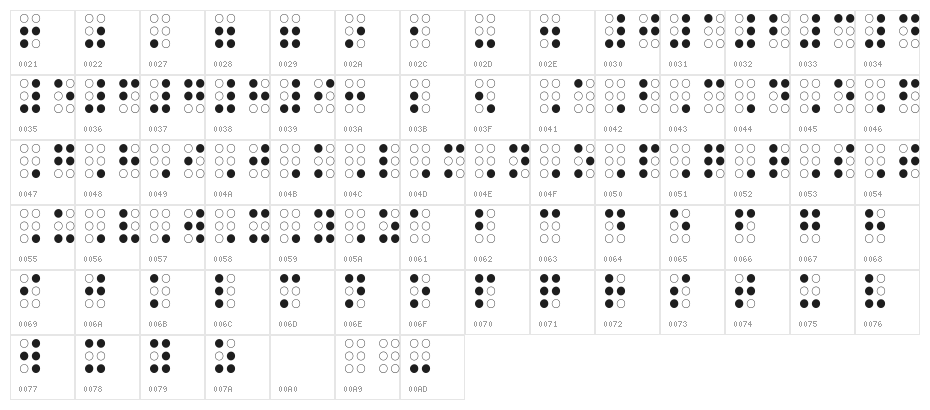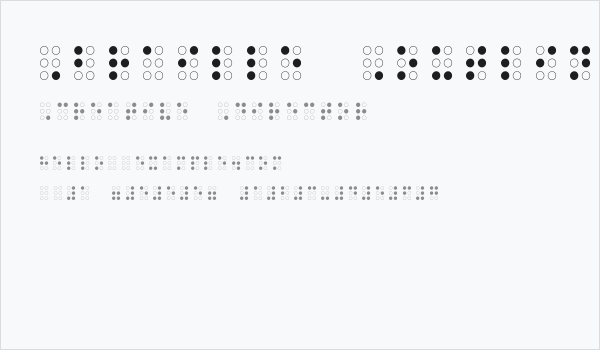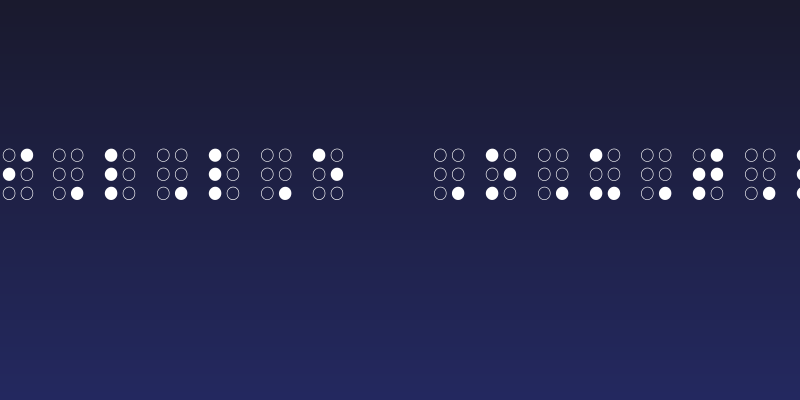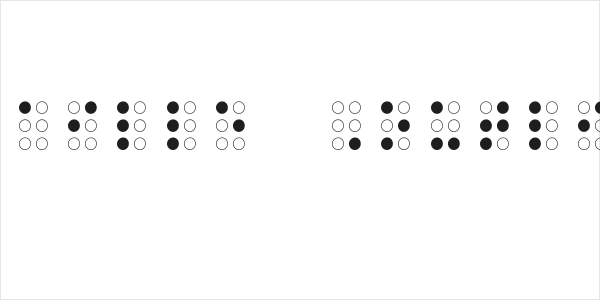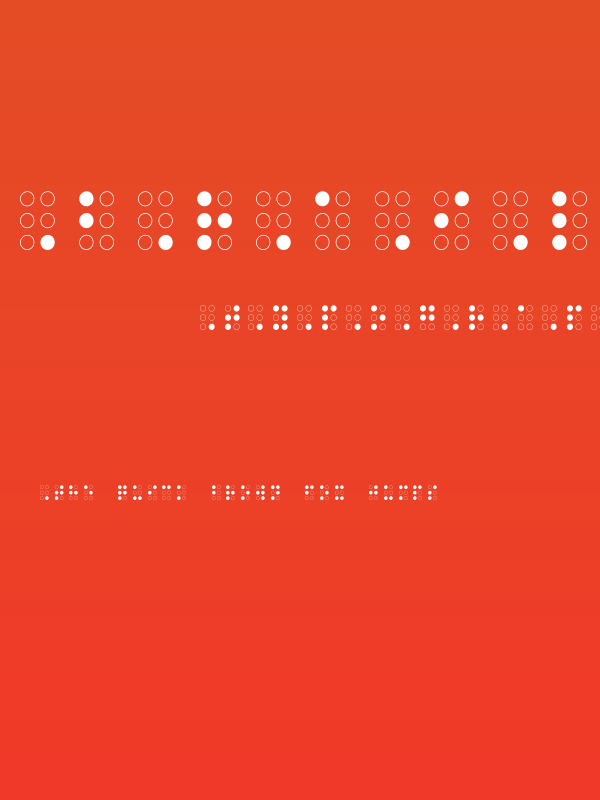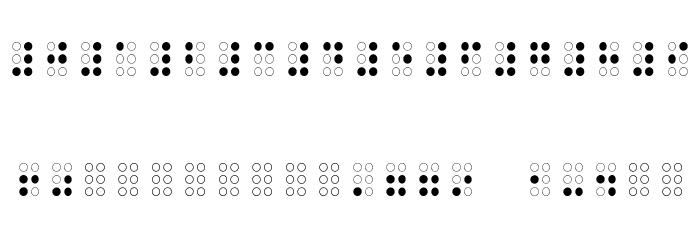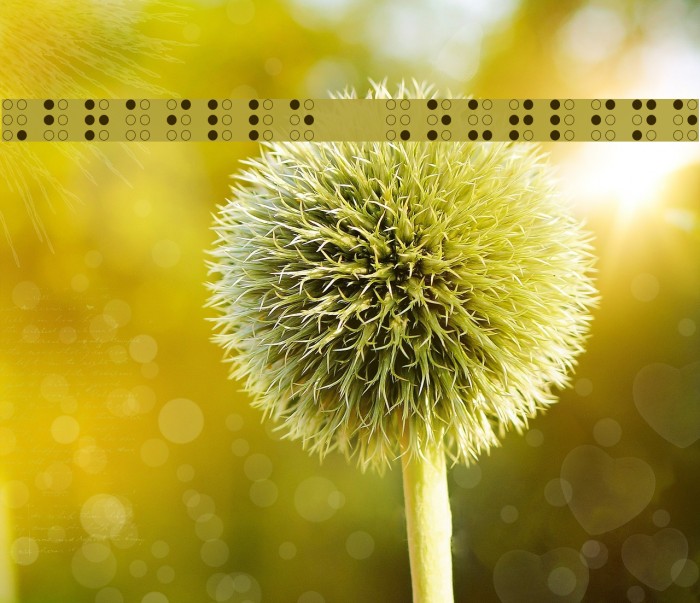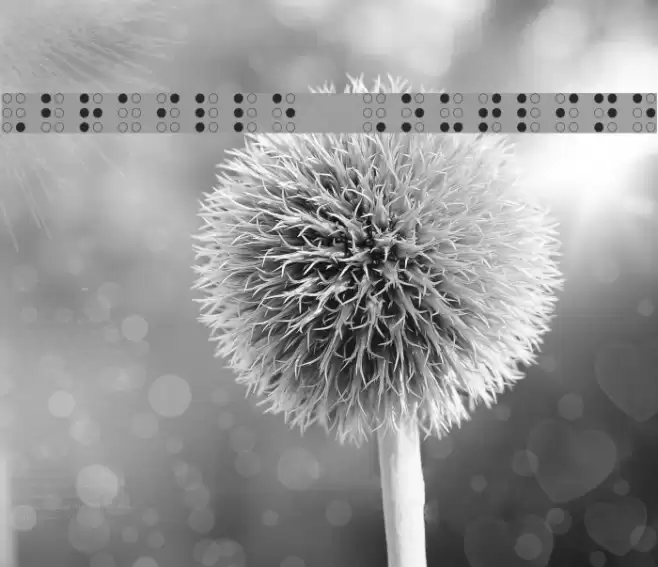
Braille Outline Font
| 全体的なスタイル | Functional, Accessibility-focused |
| 用途 | Educational materials, Accessibility tools |
| おすすめプロジェクト | Ideal for educational materials for the visually impaired, accessibility tools, and inclusive design projects. |